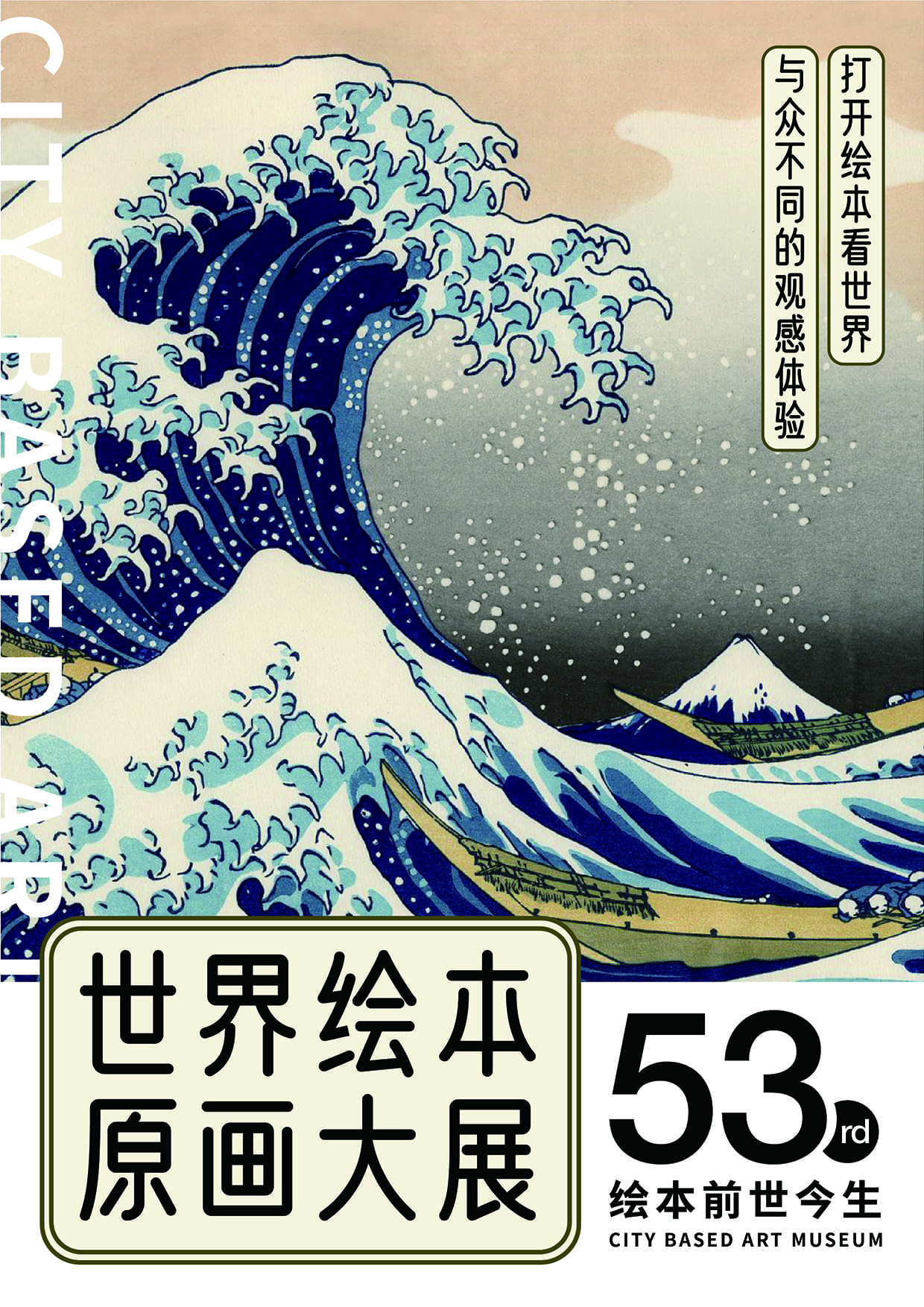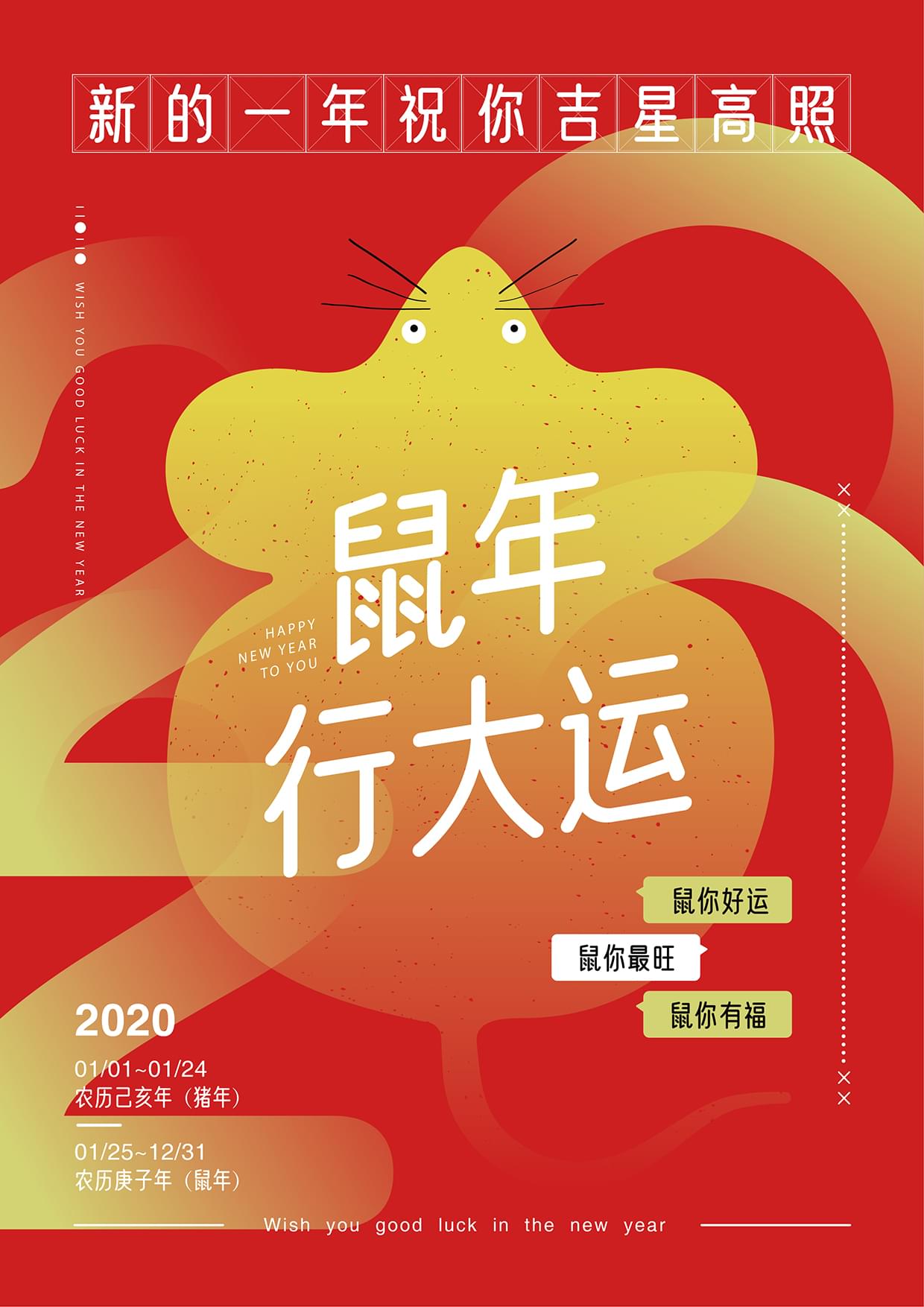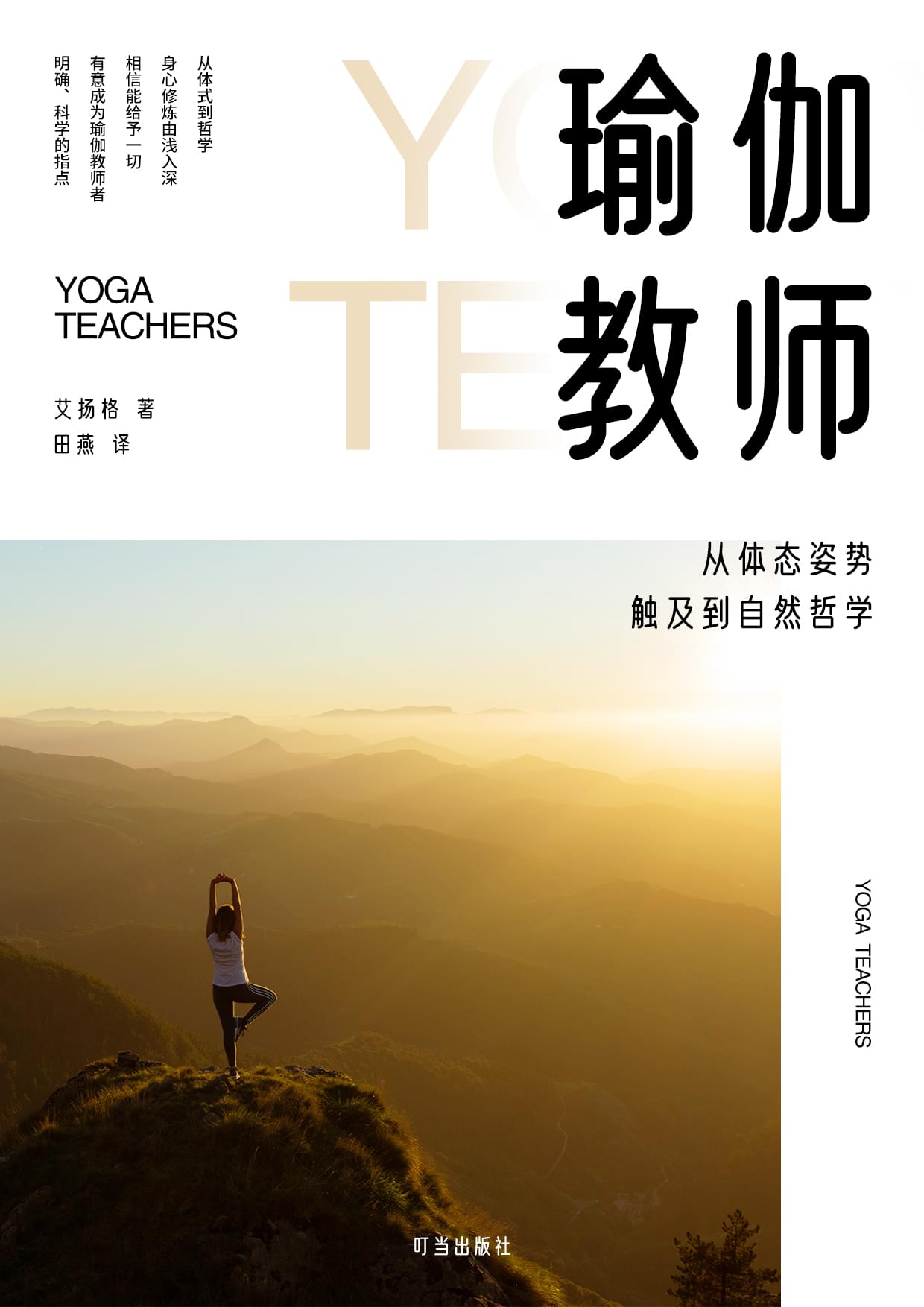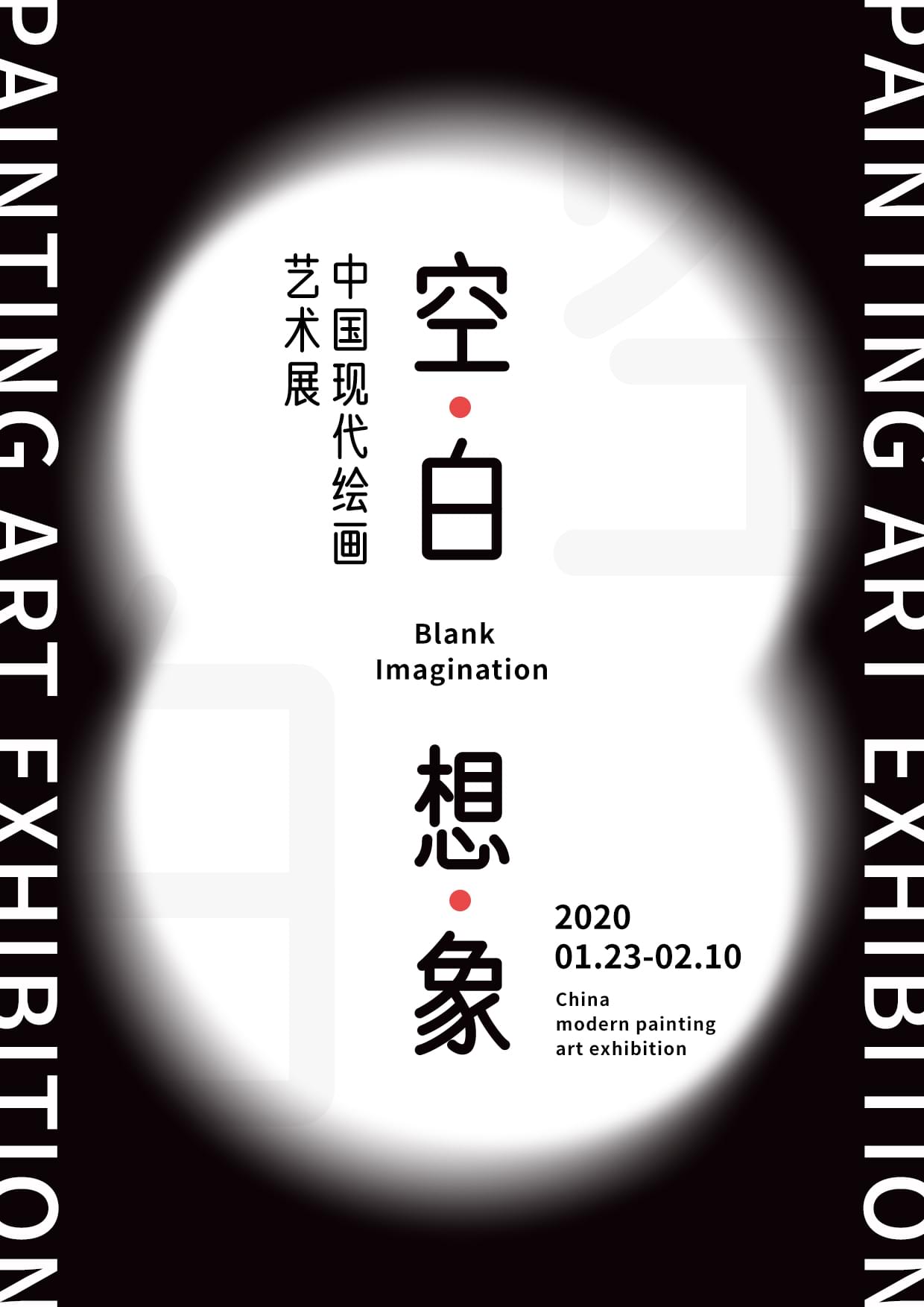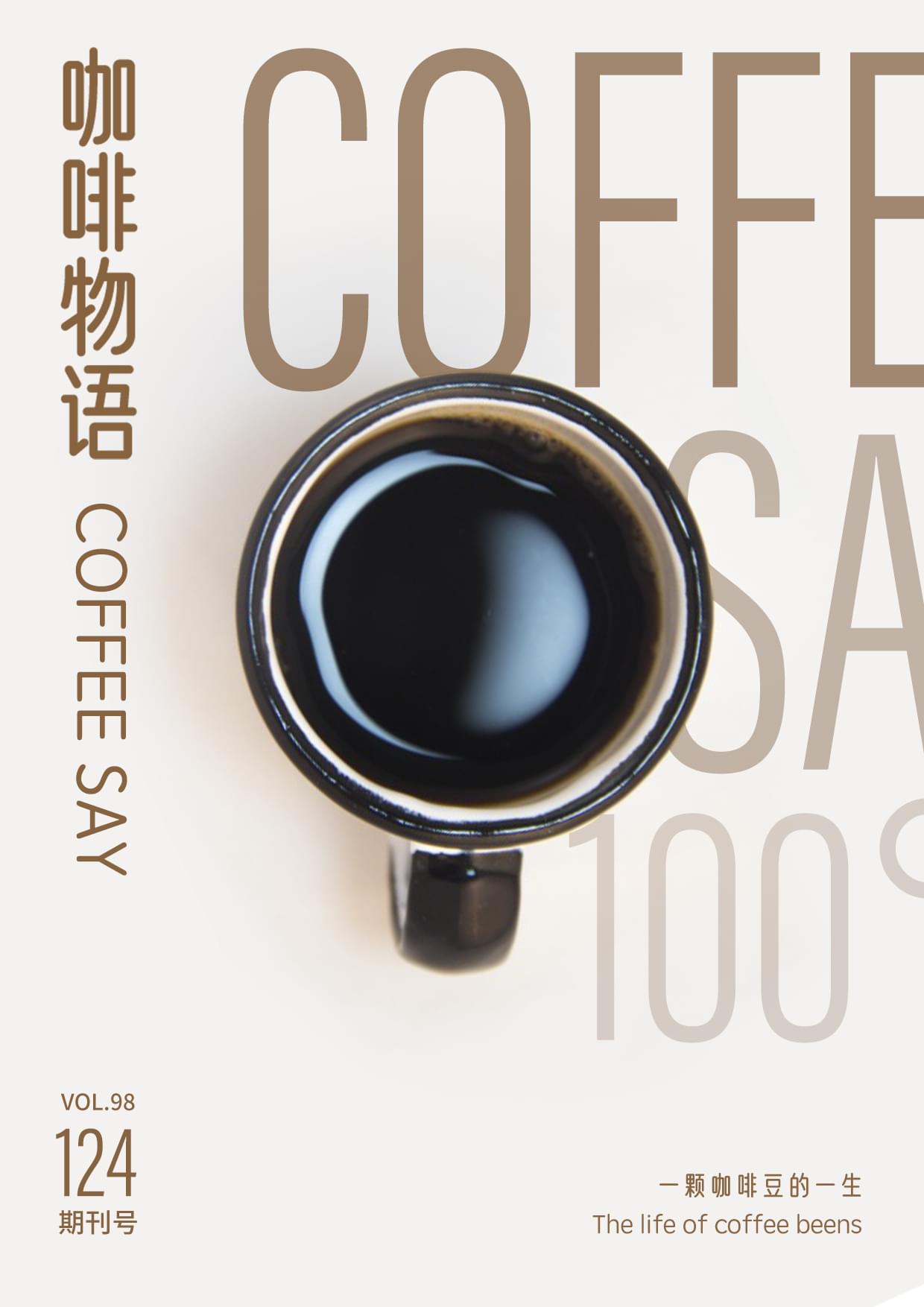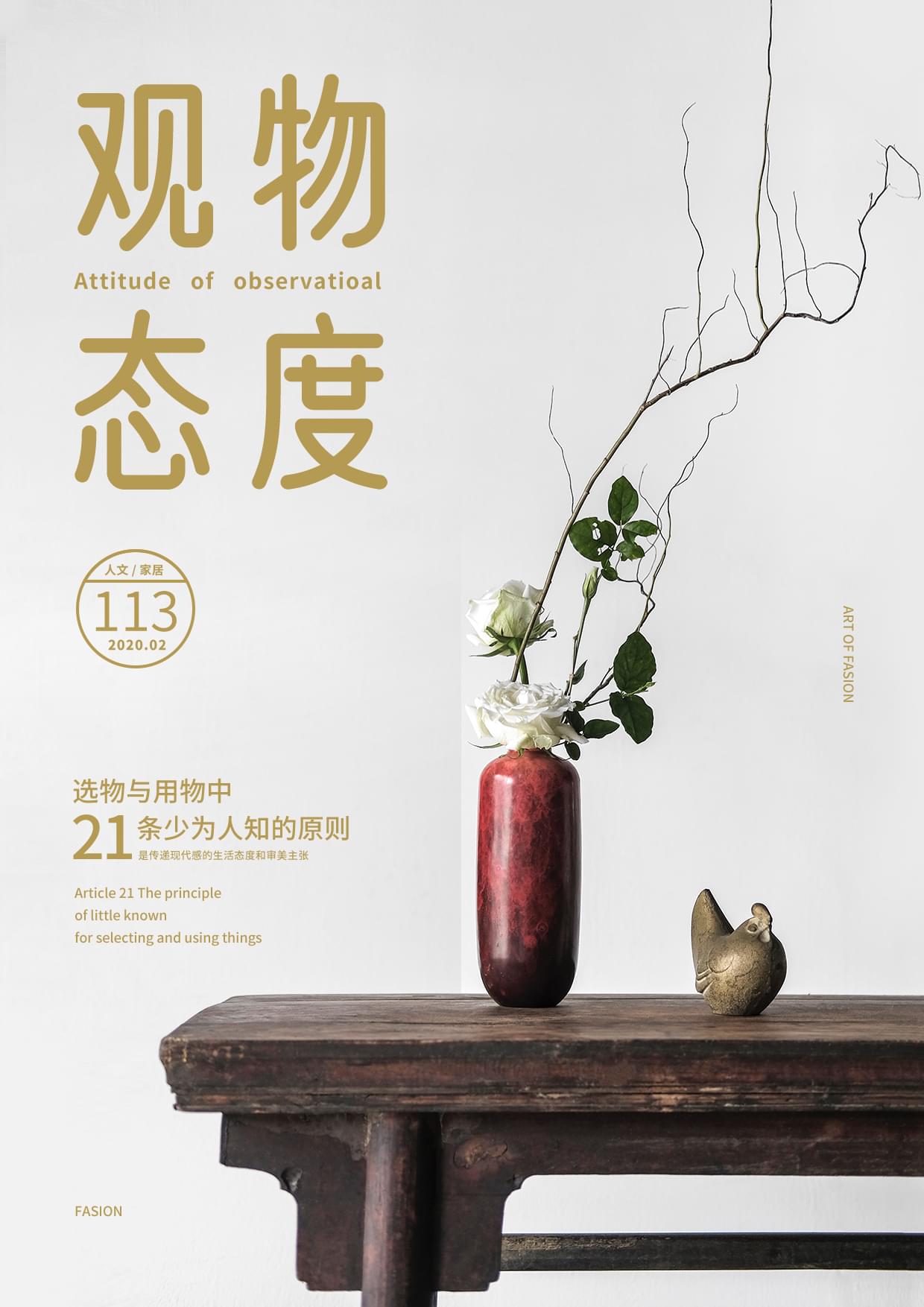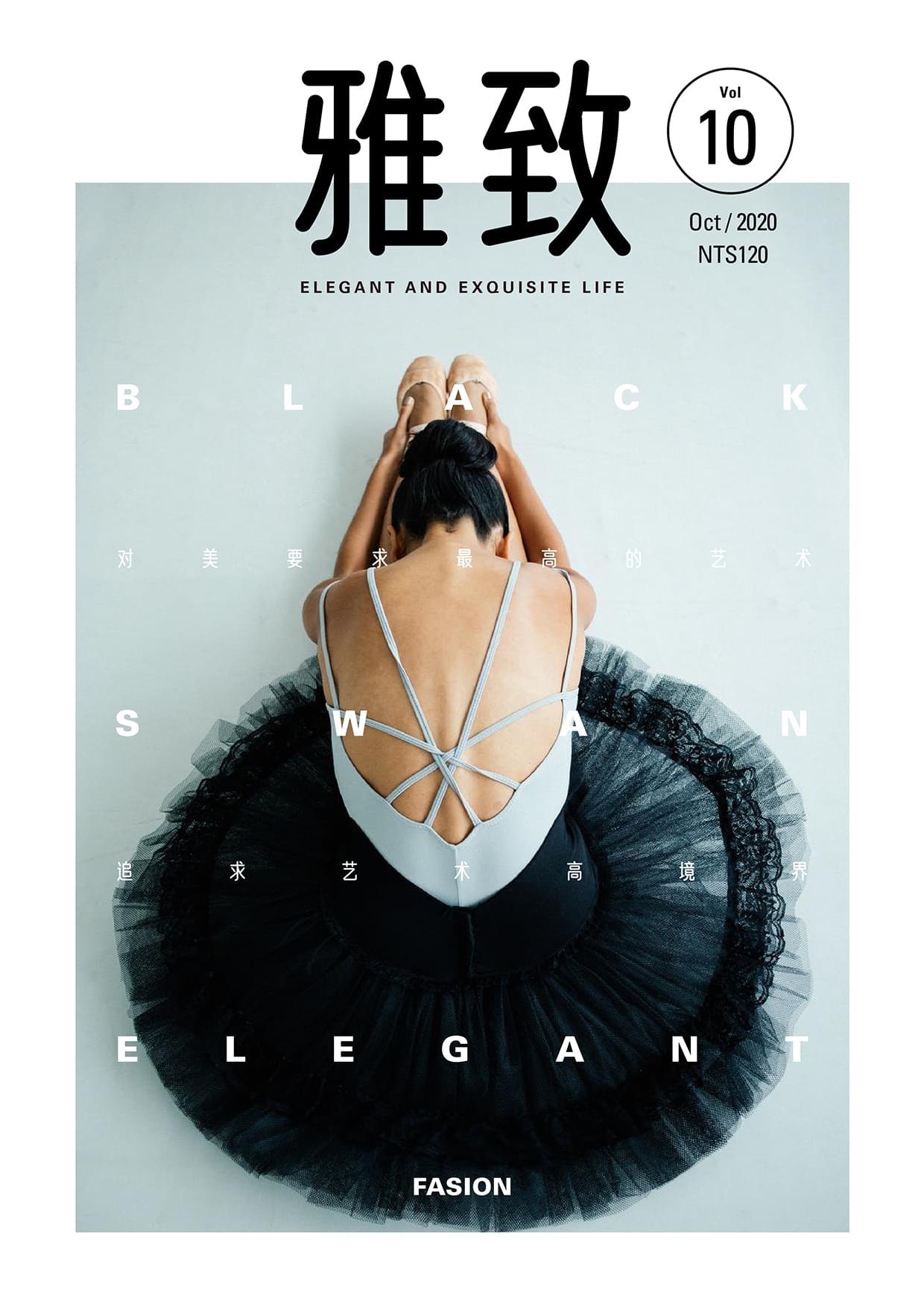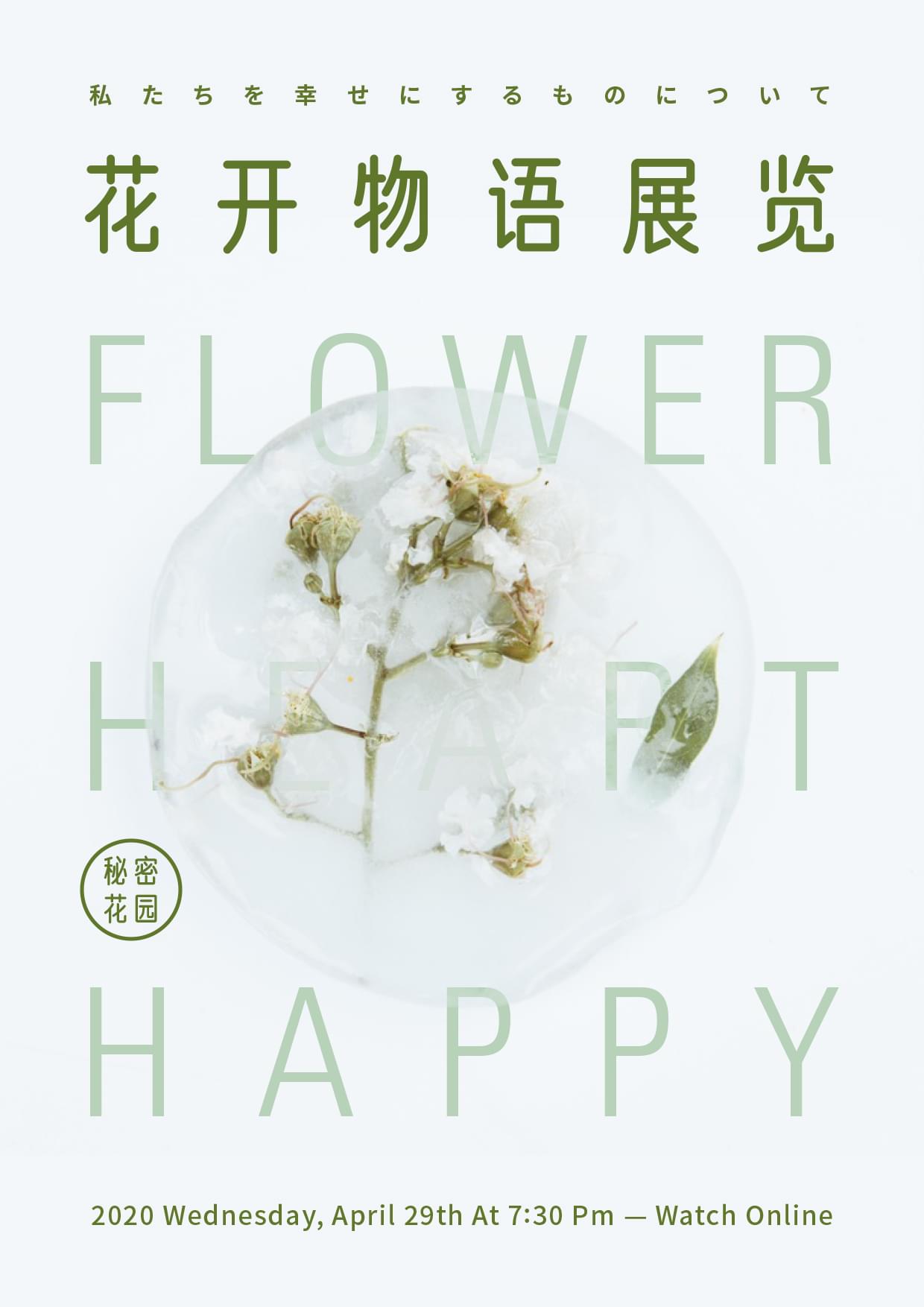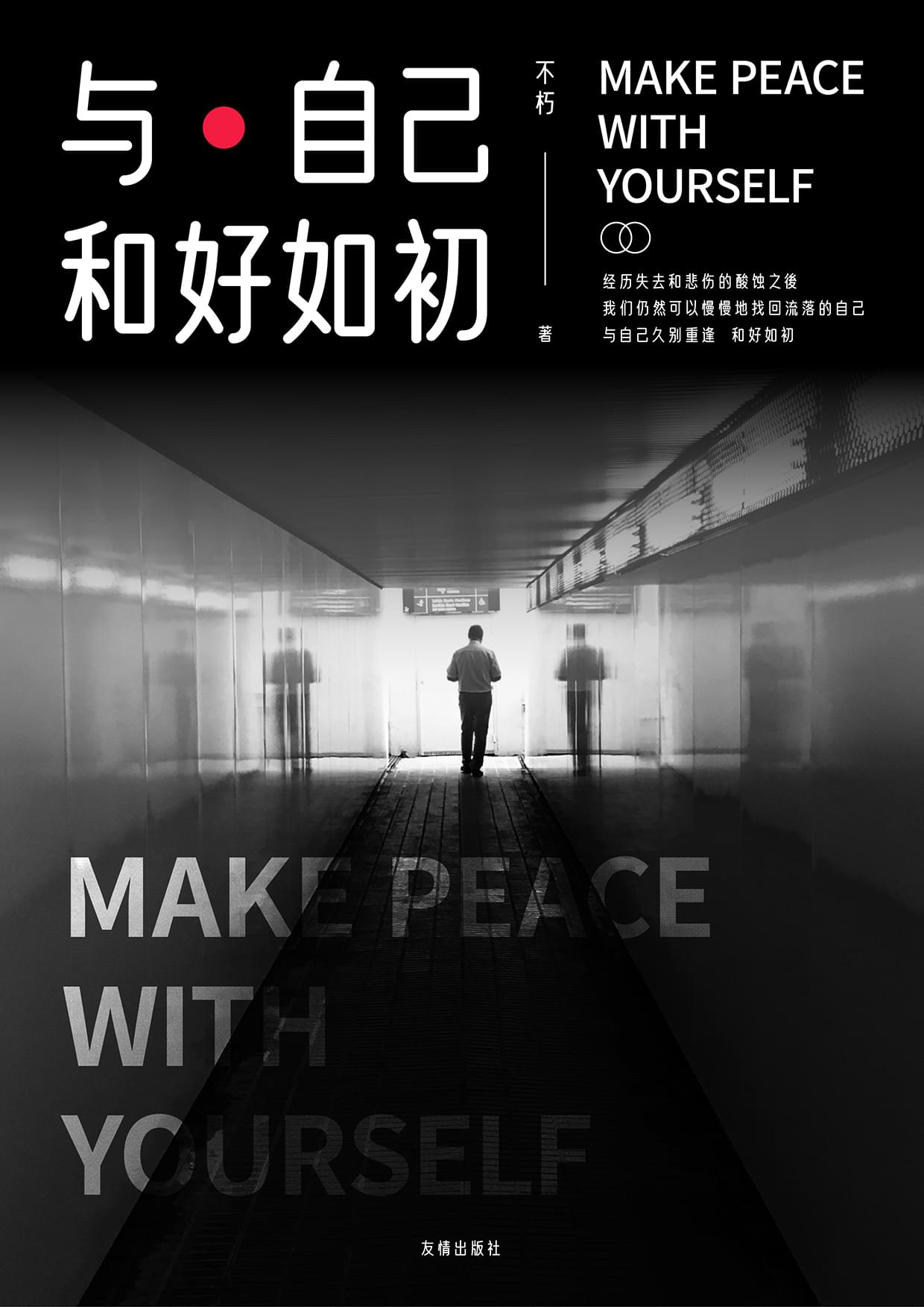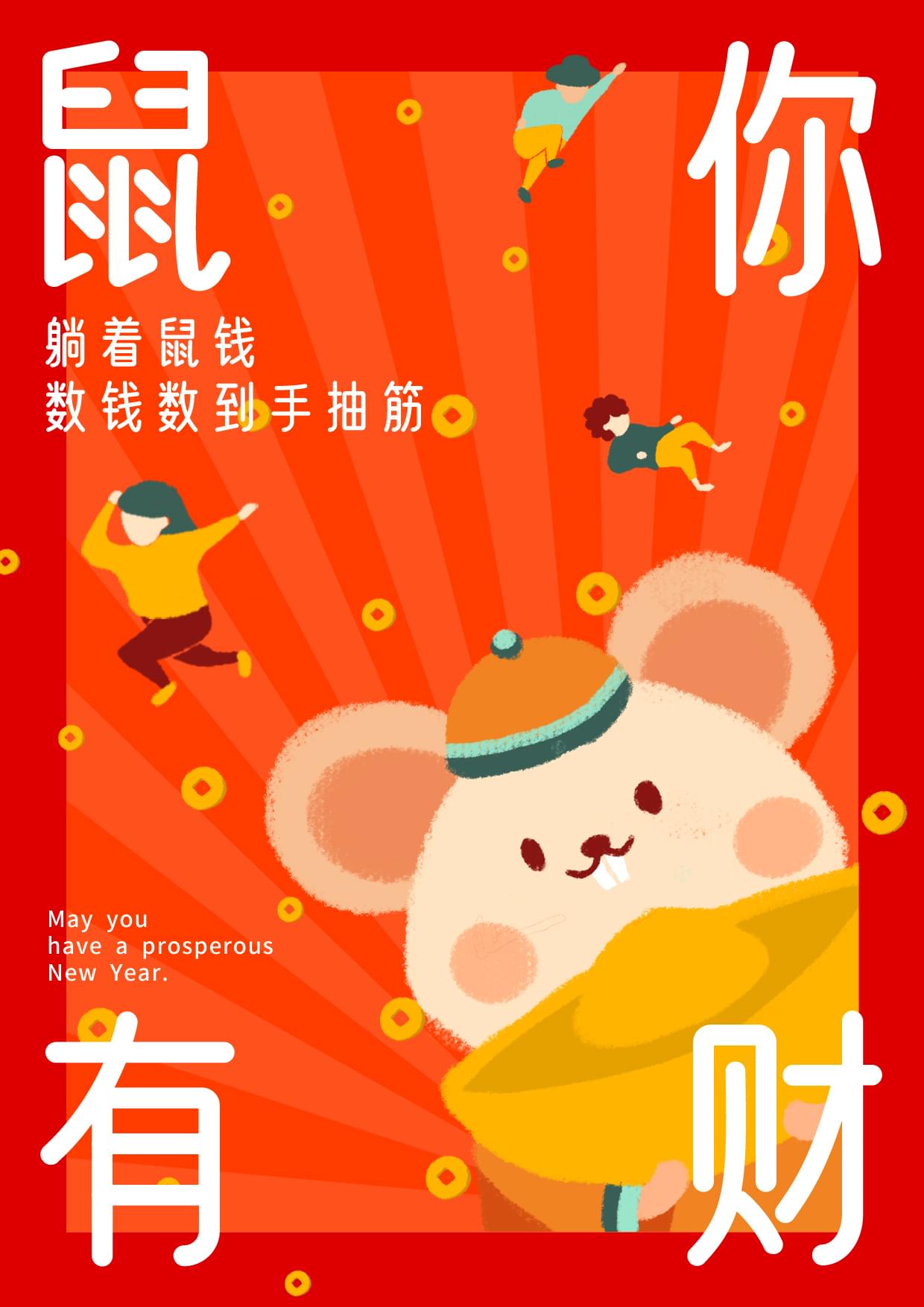
很开心能看到大家对这款字体的认可。为了不辜负设计师们的厚爱,我们从年前就一直在紧锣密鼓进行第二款「免费可商用」中文字体的制作,今天终于面世了。
优设好身体
需要强调的是,这款字体的命名和风格去年 10 月份就定下来了。
优设(浪漫的)初衷是希望设计师们用了这款字体,能减少改稿的次数,少点熬夜有个好身体。现在遇上疫情,更是成为我们对每个人的祝福,希望大家都像这款字体名字一样,平平安安有个好身体!
这款字体从风格定型到正式发布,历经100 多天,要特别感谢联合出品方字由平台。优设在完成前期300多个基础字型、字母及符号的创意与规范后,字由特意邀请了一群优秀的字体设计师,包括阿里巴巴普惠体设计师陶一泓、汉仪阿尔兹海默病体设计项目负责人卢鑫亚、汉仪锐智字体设计师石凯等,从字库角度出发,完善优化字型,完成了6000多个字型的制作,并用了大量时间来进行产品化和字体细节方面的优化。
设计思路
用过「优设标题黑」的设计师肯定记得,那是一款兼具速度感和力量感,沉稳有力的标题字。而「优设好身体」恰恰和它截然不同,一个扁平一个瘦高,一个刚猛一个温柔,设计师笑称“它俩是一对”。
「优设好身体」是一款亲和力、现代感极强的专业美术标题字体。它以圆体字型为基础,通过瘦高的字面、偏向几何的曲线,让整宽字体富有亲和力和时尚感。在同样的面积里,更窄的字面就意味着能容纳更多的信息,所以这款字体非常适用在需要体现亲和力与时尚感的各类品牌宣传广告和产品包装设计的标题上。
应用场景
海报设计篇
书籍杂志篇
Banner 篇
文字组
LOGO 篇